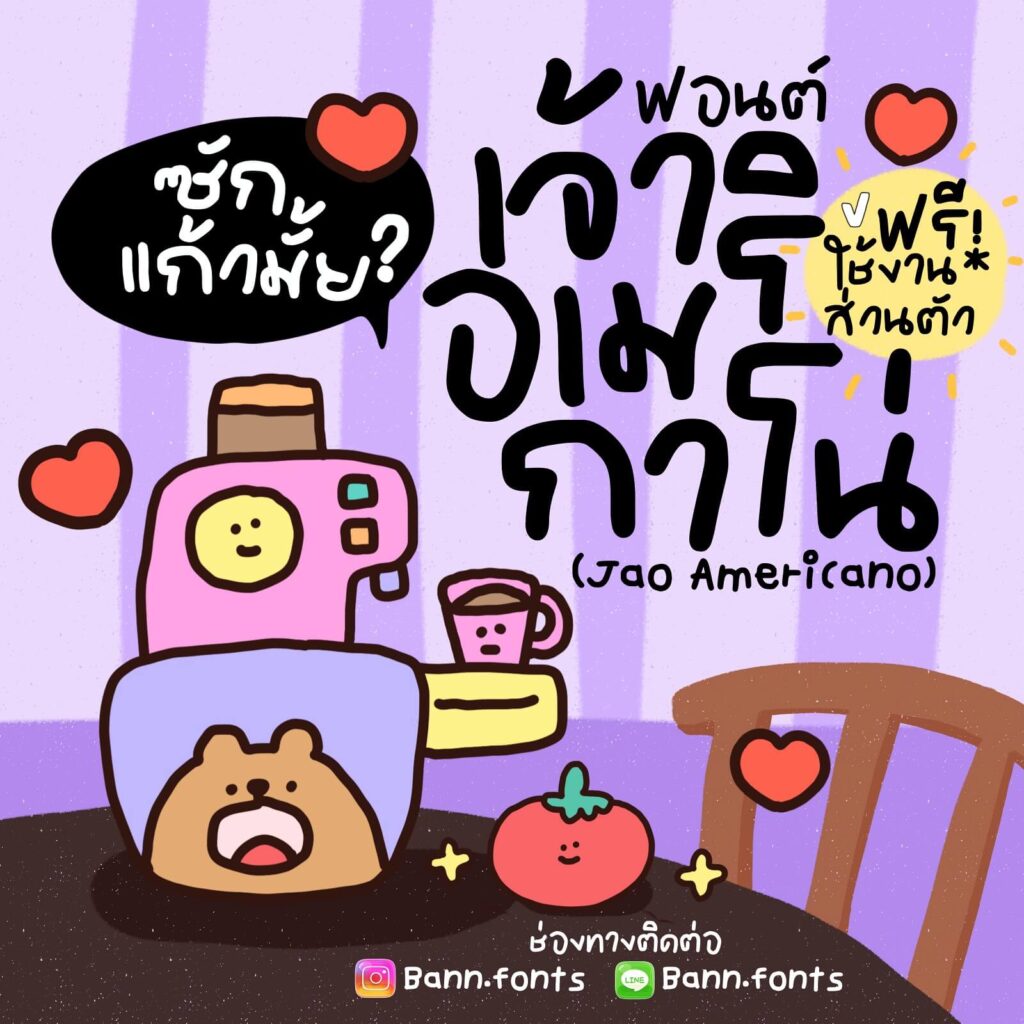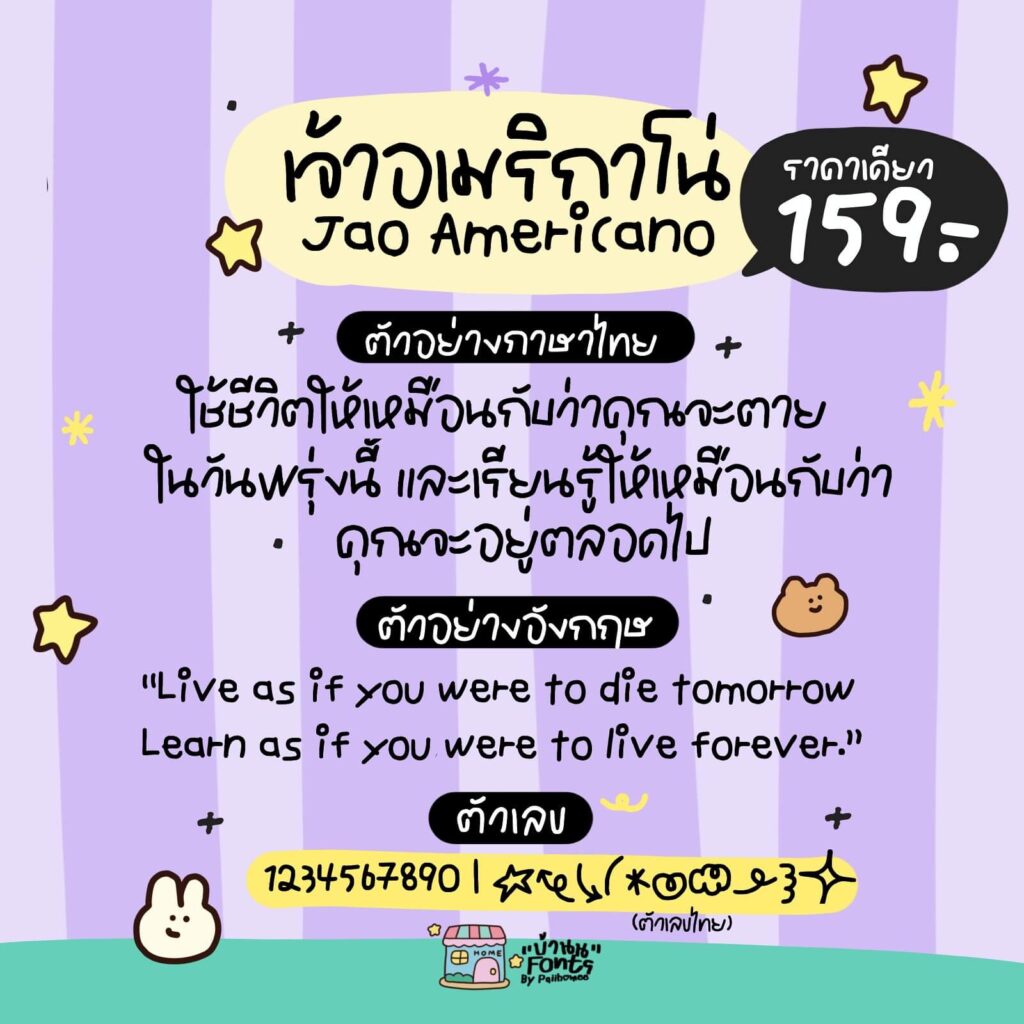
ฟอนต์เจ้าอเมริกาโน่ – แจกฟรี! สำหรับใช้ส่วนตัวเท่านั้น สำหรับน้องๆ พี่ๆ ที่ชอบฟอนต์ลายมือไม่มีหัว นำไปใช้งานไดหลากหลาย ทั้งทำคลิป แต่งรูป จดโน้ต จดบันทึก หรือส่งงานอาจารย์ ก็เริ่ดสุดๆ
อ่านง่าย ฟิลเขียนเองที่ไม่ได้เขียนเอง
เจ้าอเมริกาโน่ (JaoAmericano)